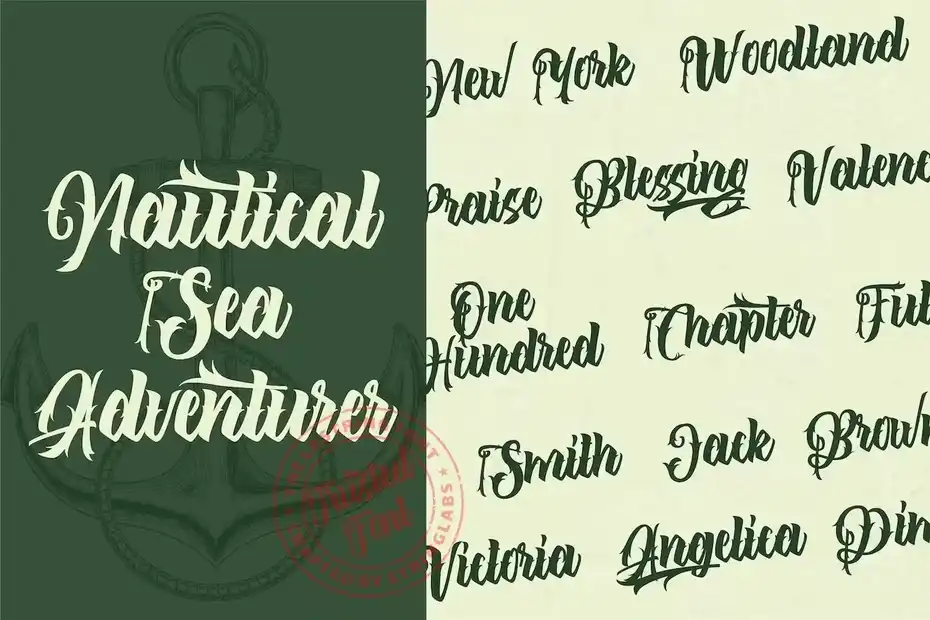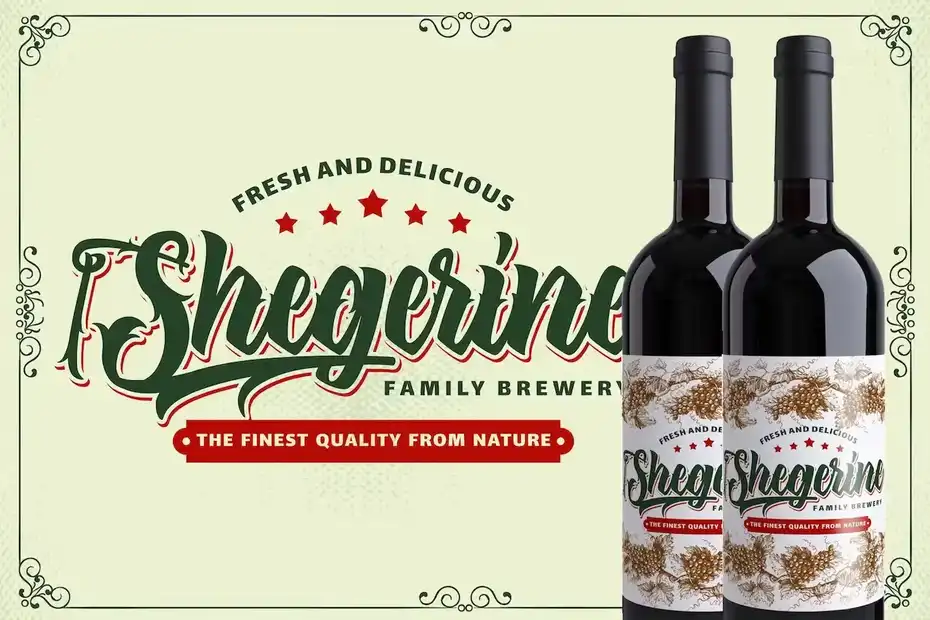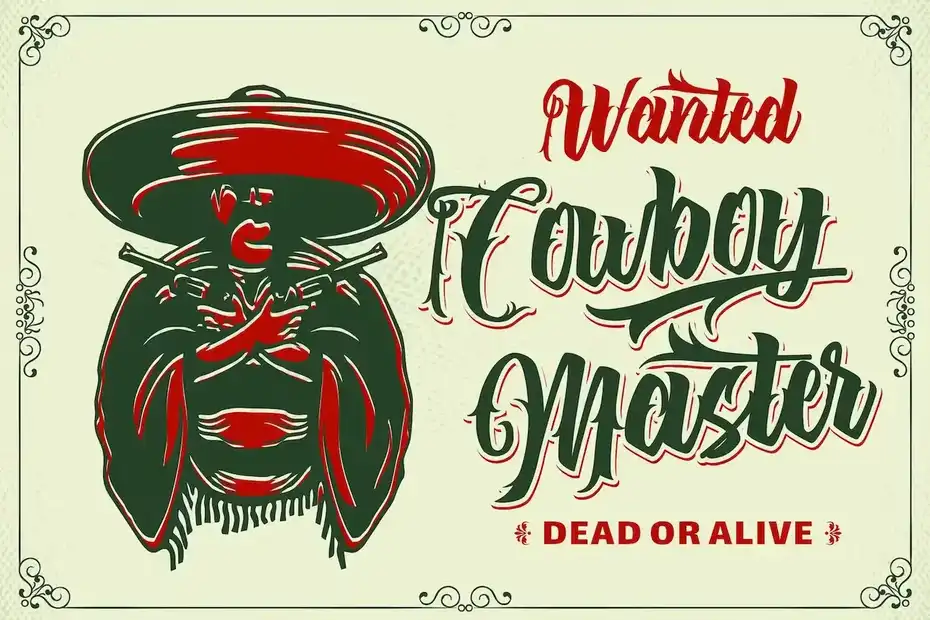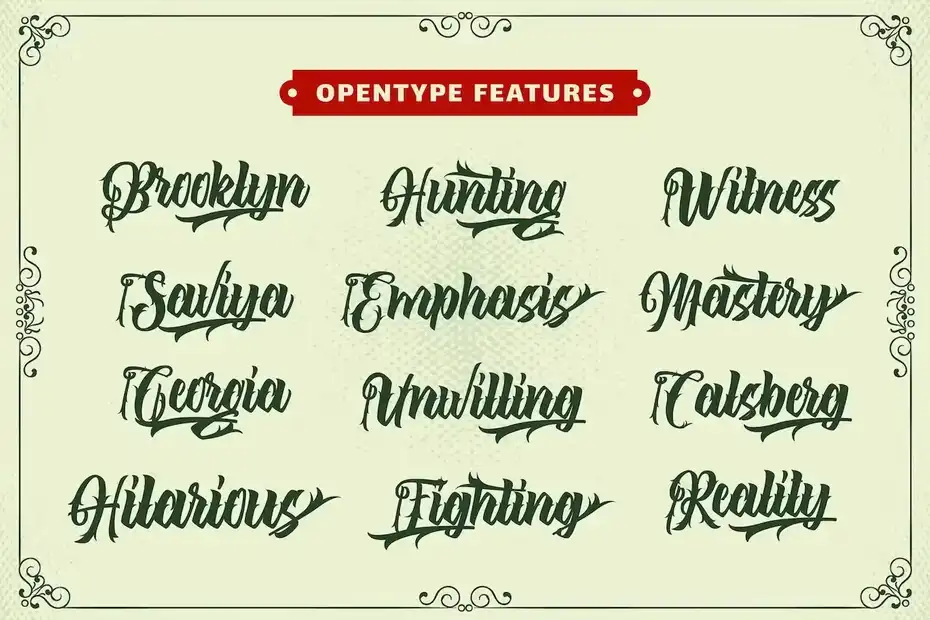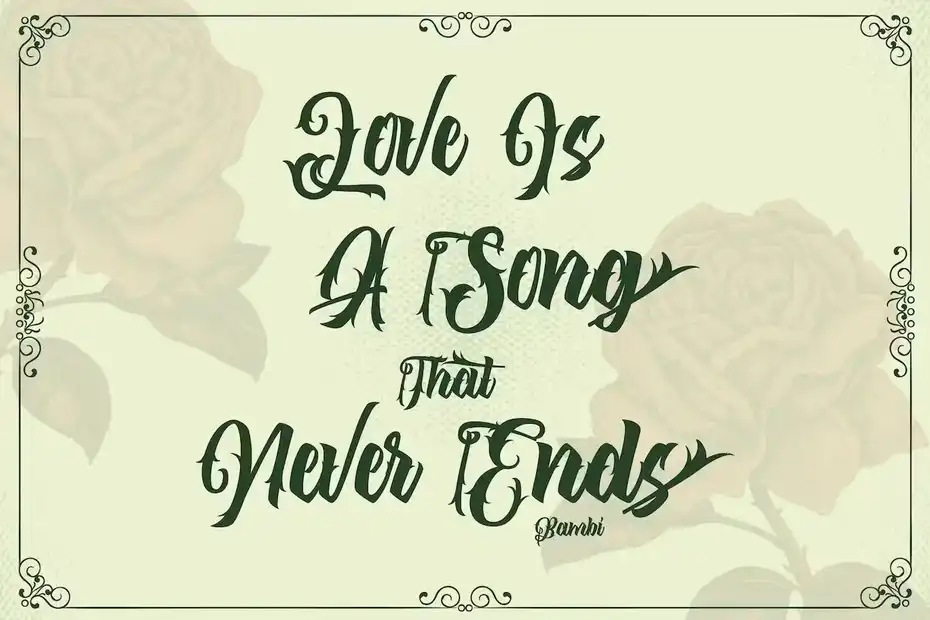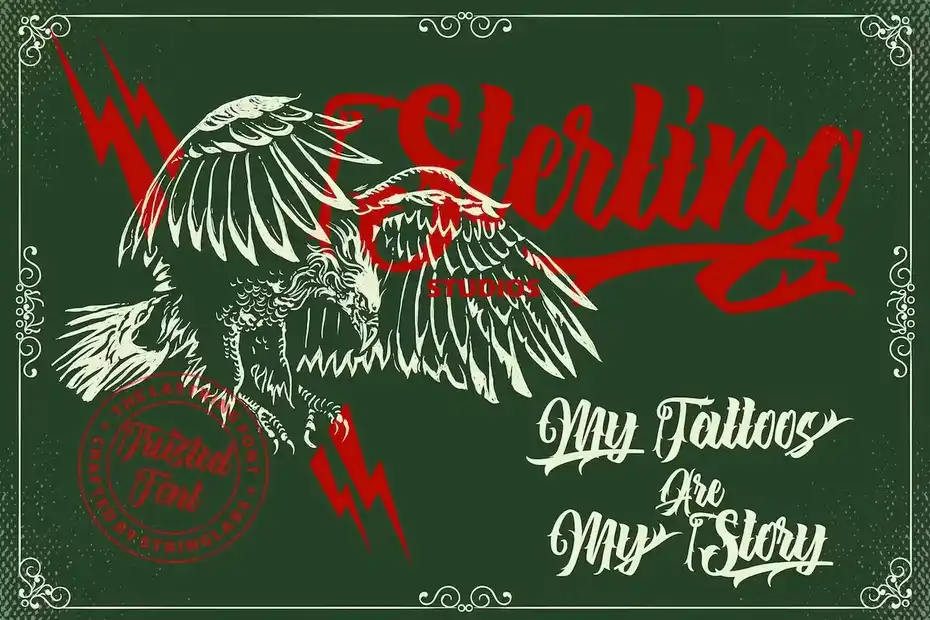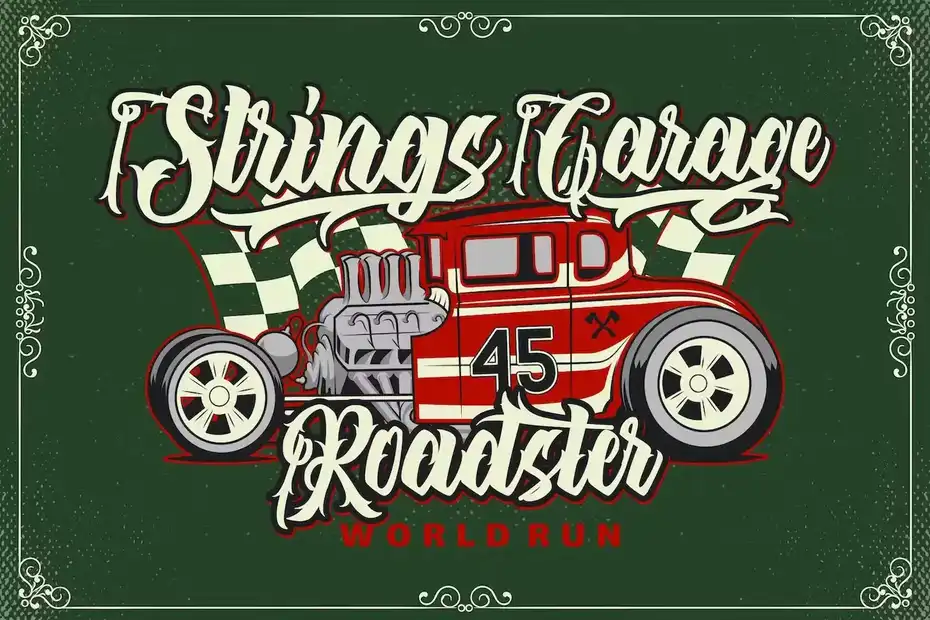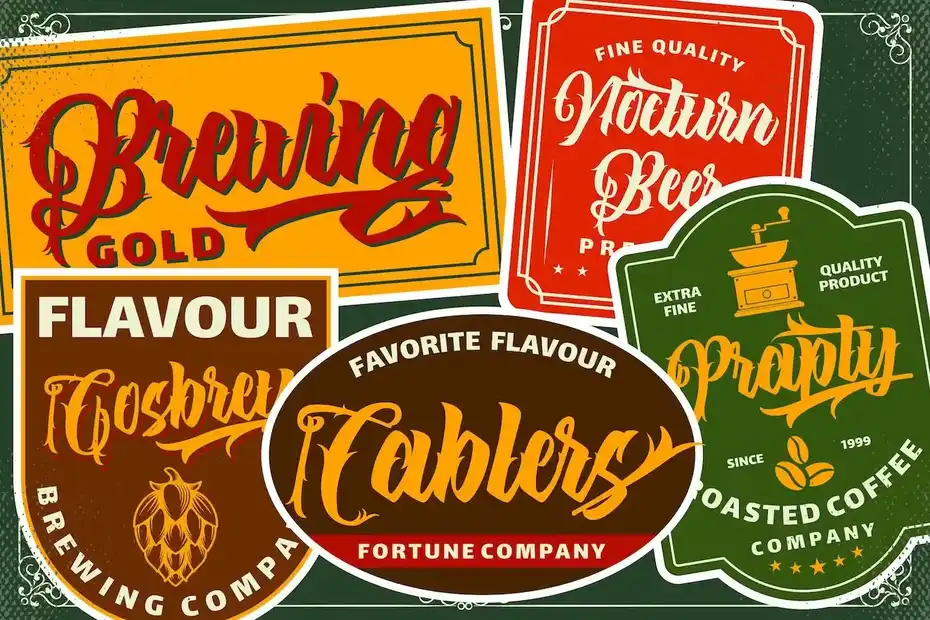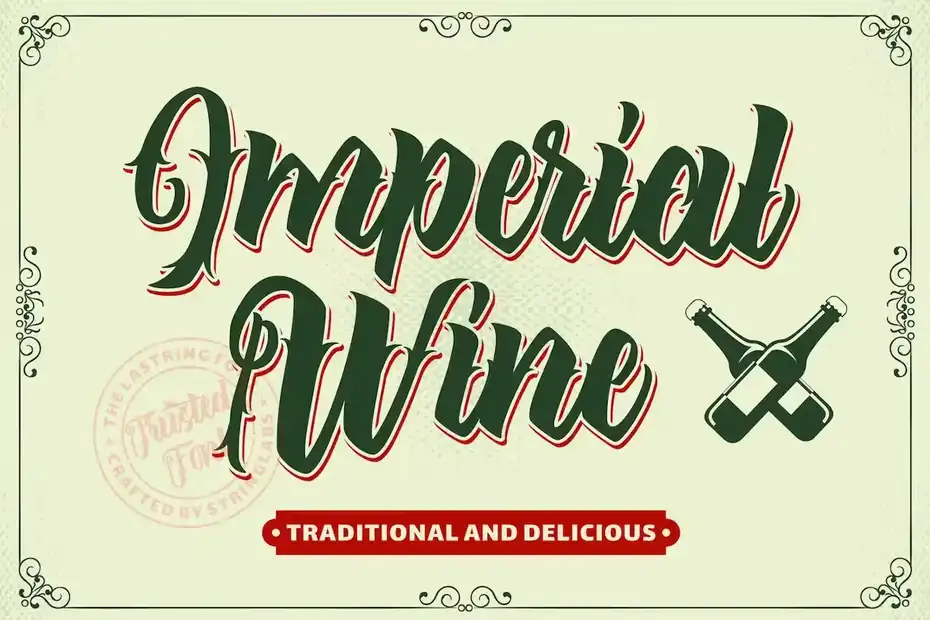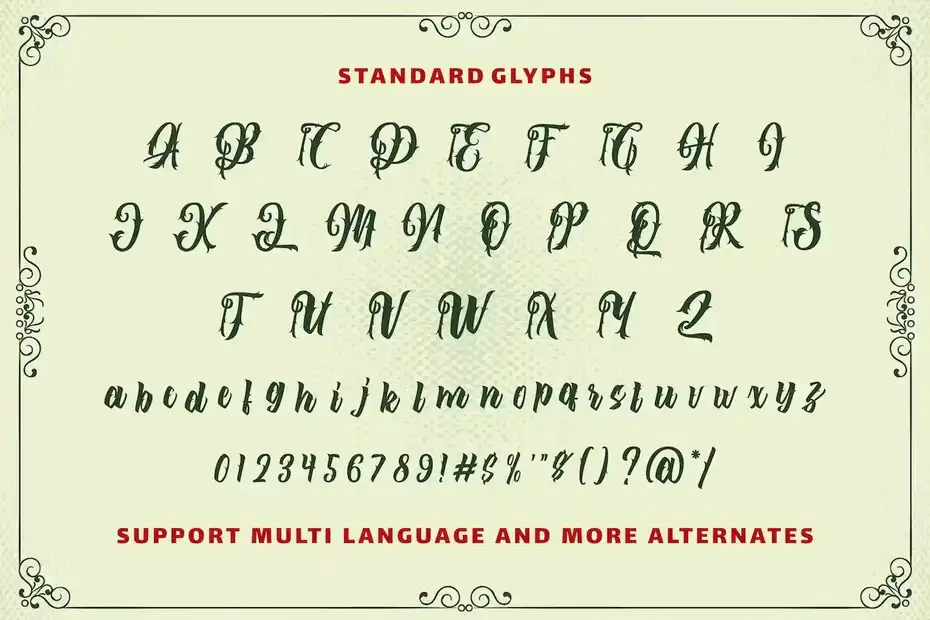
دانلود فونت انگلیسی تاتو The Lastring – Tattoo Script Font
فونت انگلیسی تاتو The Lastring – Tattoo Script Font : این مجموعه شامل یک فونت انگلیسی کلاسیک است که برای تاتو، برندینگ، طراحی تیشرت، بسته بندی محصول و غیره مناسب میباشد.
• عنوان مجموعه: The Lastring – Tattoo Script Font